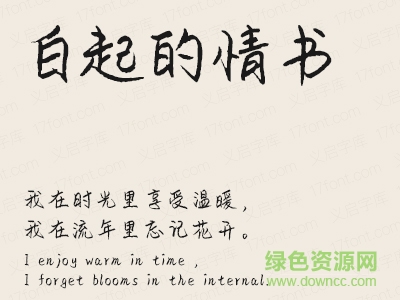
白起的情書(shū)字體是一款義啟字體出品的情書(shū)字體,喜歡玩戀與制作人的朋友們不要錯(cuò)過(guò)了,用這款字體寫(xiě)作、文章更有味道喲。歡迎大家來(lái)綠色資源網(wǎng)踴躍下載使用!
我不會(huì)情話,不會(huì)撩妹,我只會(huì)迎著風(fēng),尋找你的方向。